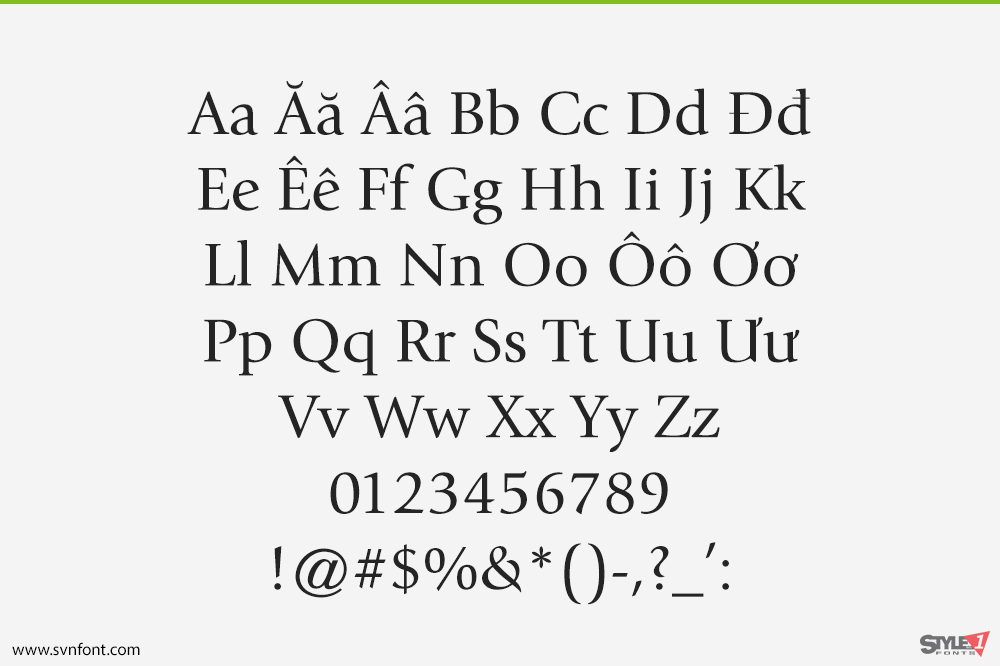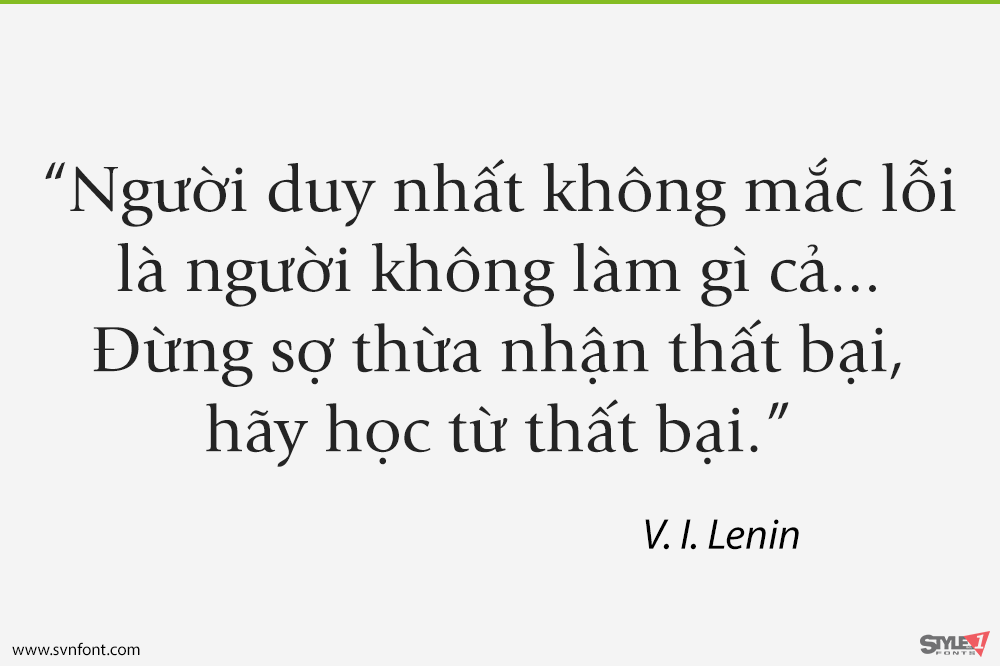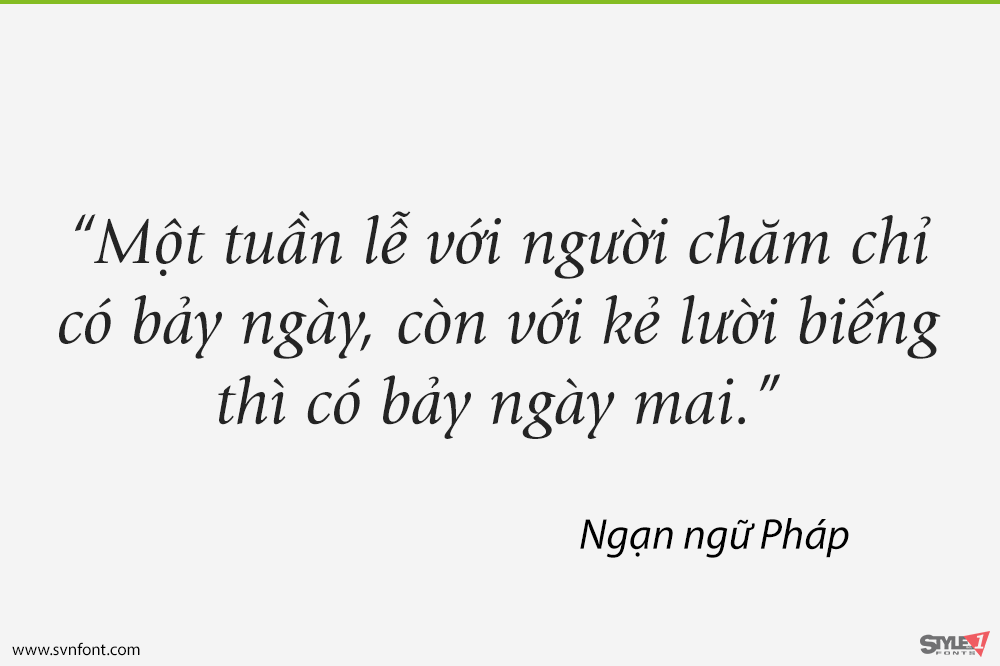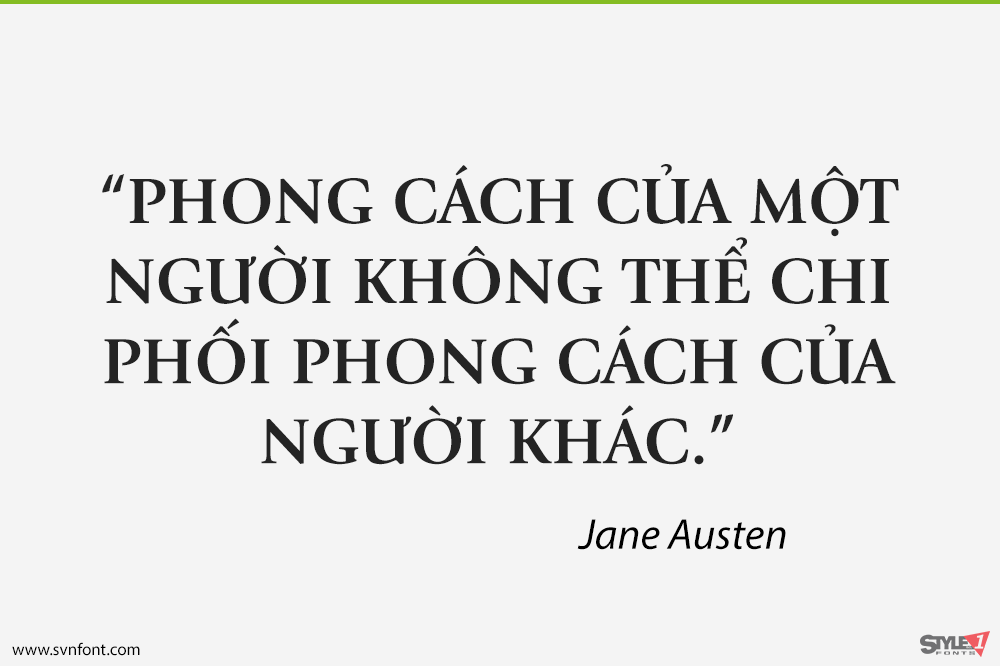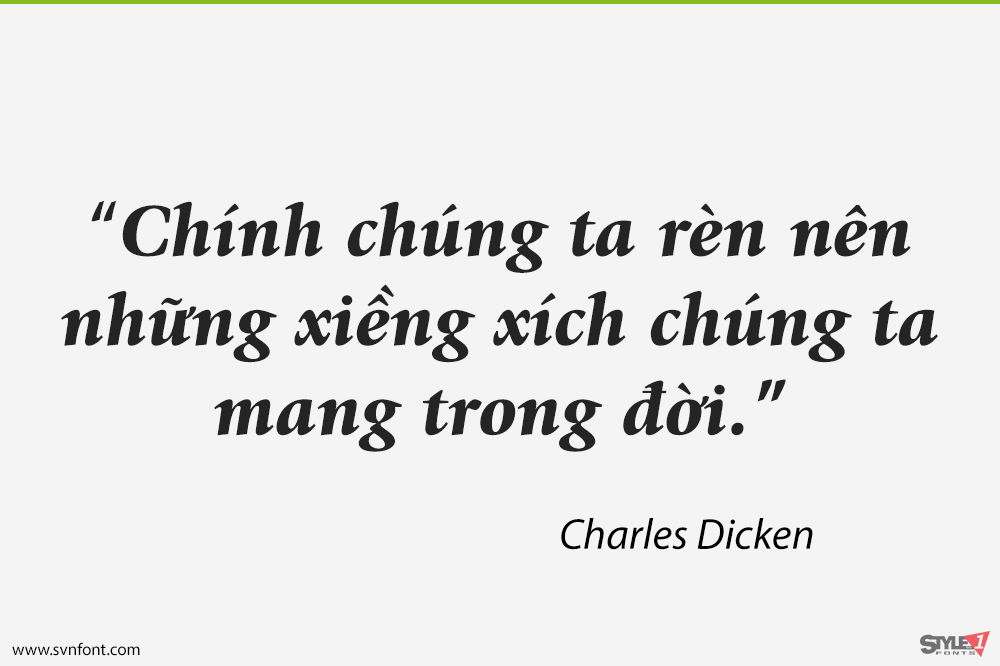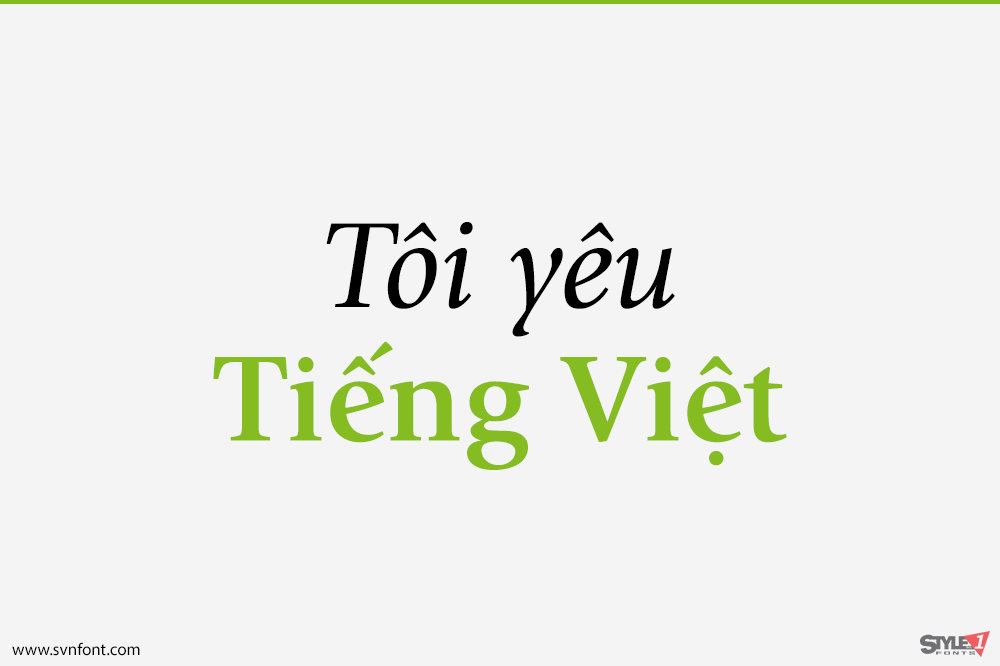
ITC Giovanni là tác phẩm của nhà thiết kế kiểu chữ người California, Robert Slimbach. Mục tiêu của ông là tạo ra một phông chữ có tỷ lệ kiểu cũ cổ điển nhưng vẫn mang đậm nét đương đại. ITC Giovanni mang cảm giác hiện đại với các nét lên (ascenders) và nét xuống (descenders) được rút ngắn một chút, chiều cao x-height lớn hơn một chút và các chữ in hoa nhẹ hơn về mặt thị giác.
Nhà thiết kế: Robert Slimbach
Nhà phát hành: ITC Inc.